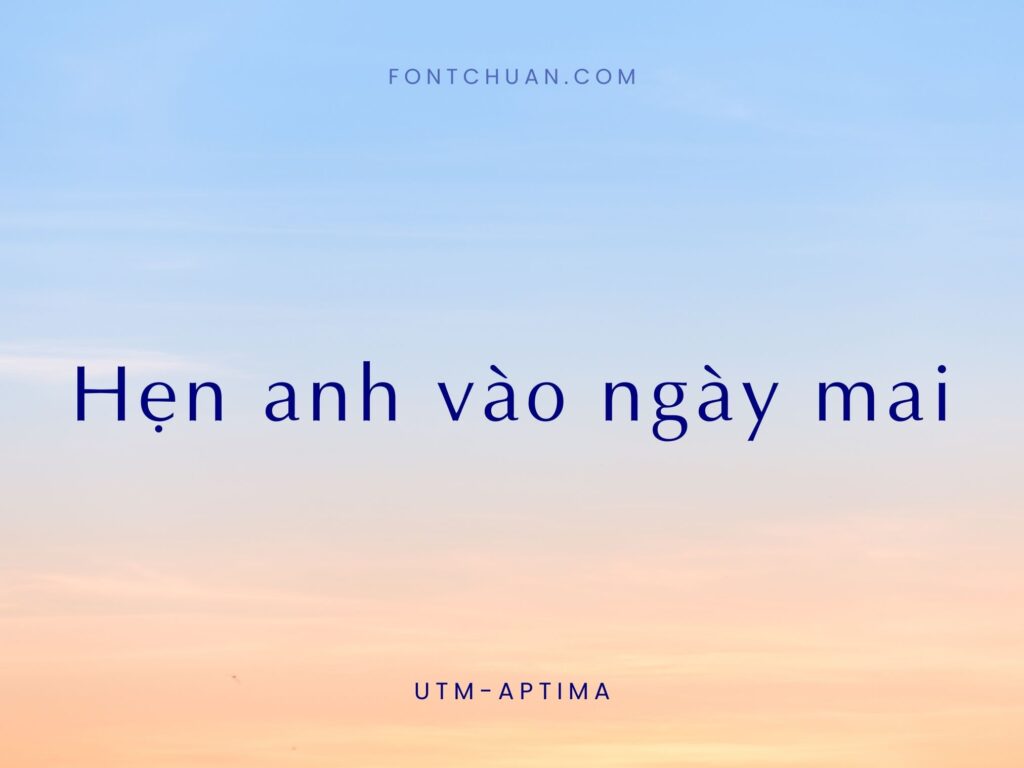
UTM Aptima là một kiểu chữ sans-serif hiện đại, mang phong cách tối giản và thanh lịch. Font này đã được Việt hóa, hỗ trợ đầy đủ tiếng Việt cùng hơn 200 ngôn ngữ khác. Thành viên của Font Chuẩn đã sưu tầm và chọn lọc font này nhằm đáp ứng nhu cầu đa dạng của bạn đọc và ứng dụng thực tế vào các dự án thiết kế.
UTM Aptima có cấu trúc chữ với các nét đều đặn, không chân, tạo nên vẻ đẹp hiện đại và dễ đọc. Font này phù hợp cho các ứng dụng như thiết kế logo, tiêu đề, bao bì sản phẩm và các ấn phẩm in ấn khác. Các ngành nghề như quảng cáo, giáo dục, bất động sản và công nghệ có thể tận dụng UTM Aptima để tạo điểm nhấn chuyên nghiệp và thân thiện trong thiết kế.